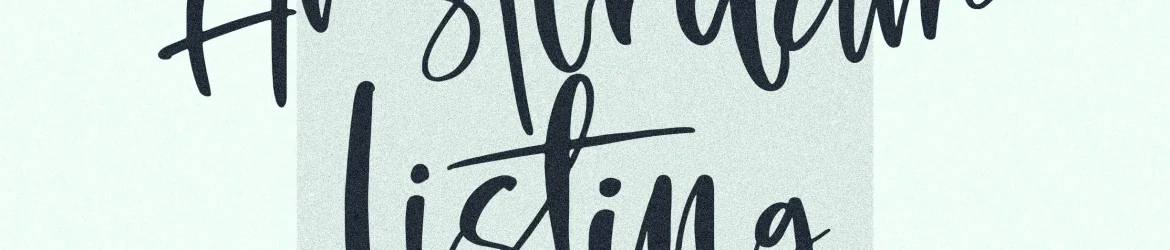
Amsterdam Listing Font
A Amsterdam Listing Font é uma elegante fonte script que se destaca na categoria das fuentes manuscritas, perfeita para aplicar seu próprio toque pessoal e único a uma variedade de projetos. Seja você um designer criativo ou um artesão da homewares que busca personalizar as embalagens de seus produtos com notas de arte, essa fonte é sua escolha certa. Com seu arretado estilo manuscrito, a Amsterdam Listing Font oferece flexibilidade para criar designs de marcas e identidades visuais modernas, além de produzir resultados profissionais em mugs, capas de livros, etiquetas e materiais promocionais. Seja uma t-shirt personalizada com um único quote ou um convite de casamento detalhado, este fonte é ideal para qualquer projeto que exigirá um toque cuidadosamente elaborado. Além disso, a Amsterdam Listing Font também oferece uma ampla gama de aplicabilidades para designers gráficos. Você pode usá-la em posters de divulgação ou na criação de design exclusivo para sua próxima publicação. Seja uma imagem fotográfica que desejar editar e incluir o seu toque pessoal, ou até mesmo um logotipo customizado com um toque único de letra manuscrita, a Amsterdam Listing Font é sua solução perfeita para qualquer projeto exigindo personalidade. Ainda não entrou em uma aventura de design com essa fonte? Em breve, a perspectype nos apresentará mais fuentes que combinam beleza e utilidade. Você pode confiar no profissionalismo dessa equipe para garantir que cada nova criação seja de alta qualidade, oferecendo um recurso valioso e único para qualquer designer ou artista gráfico.